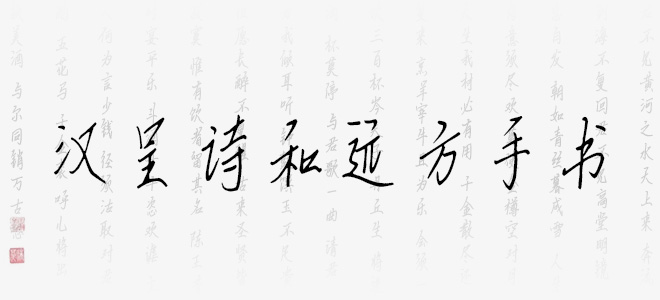
漢呈詩(shī)和遠(yuǎn)方手書(shū)字體筆觸纖細(xì),書(shū)寫(xiě)流暢灑脫,具有很好的視覺(jué)感,適合應(yīng)用于藝術(shù)設(shè)計(jì)、平面宣傳設(shè)計(jì)、網(wǎng)頁(yè)設(shè)計(jì),書(shū)法字帖等領(lǐng)域,歡迎喜歡漢呈詩(shī)和遠(yuǎn)方手書(shū)字體的朋友前來(lái)下載使用。
漢呈詩(shī)和遠(yuǎn)方手書(shū)